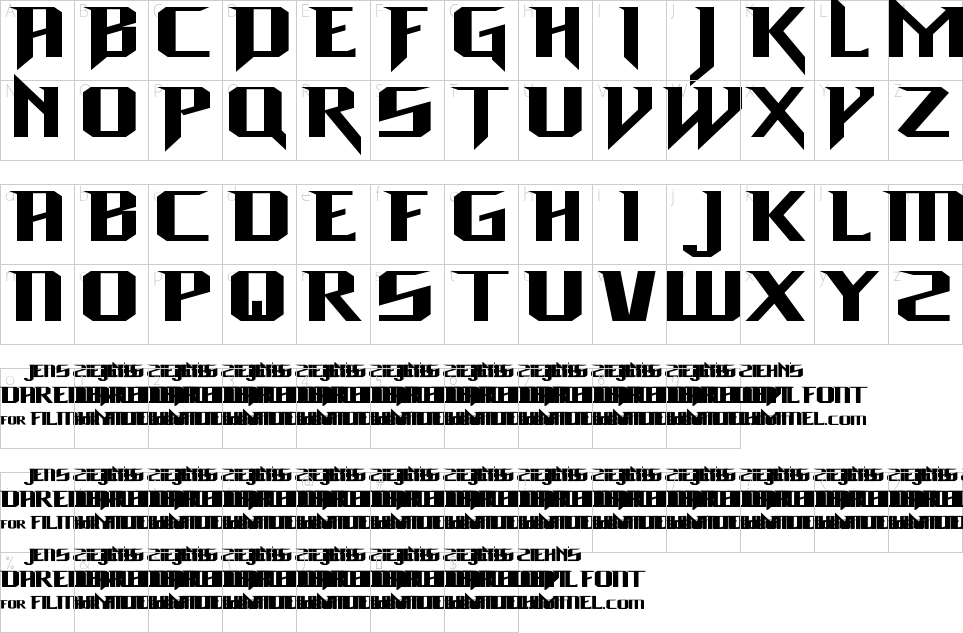
Daredevil Font
A fonte ‘Daredevil’ é uma opção interessante para quem busca uma face única e poderosa no design gráfico. Desenvolvida por Jens R. Ziehn, a ‘Daredevil Font’ foi projetada com um ar inovador e moderno que se destaca na composição de textos, especialmente em ambientes onde o impacto visual é crucial. Se você busca adicionar uma atmosfera aguçada ou icônica aos seus trabalhos gráficos, essa fonte poderia ser perfeita para você. A ‘Daredevil Font’ já foi baixada mais de 43 mil vezes e, por isso, provavelmente tem um grande número de usuários que a avaliam positivamente. Para quem está procurando uma fonte moderna com estilos distintos e uma variedade de usos para o design de interface do usuário ou design gráfico, ‘Daredevil Font’ pode ser uma escolha brilhante. Suas linhas fortes e sua capacidade de criar um impacto poderoso em qualquer projeto podem ajudá-lo a destacar-se na comunidade de designers. O nome da fonte já faz referência ao seu design forte e diferenciado, como o personagem do quadrinhos do mesmo nome.